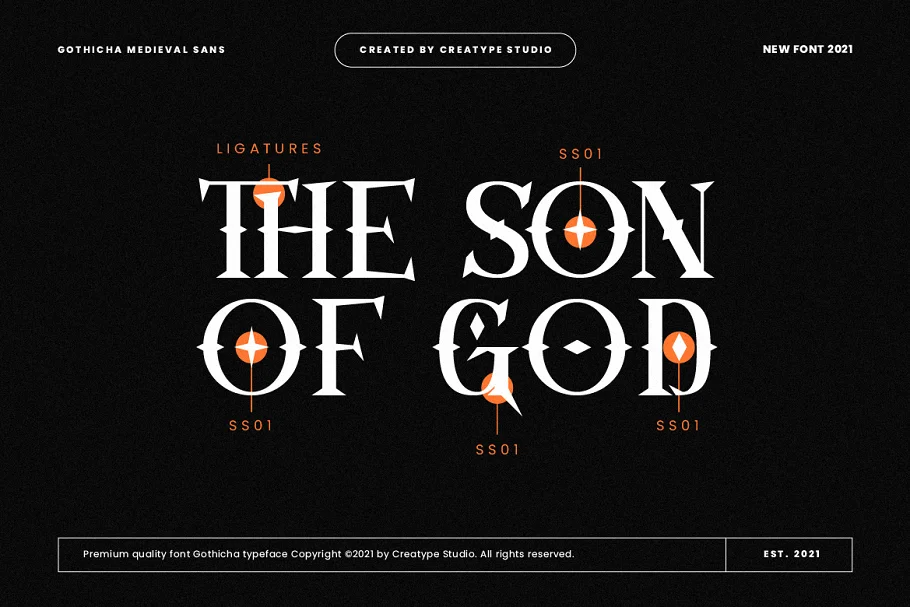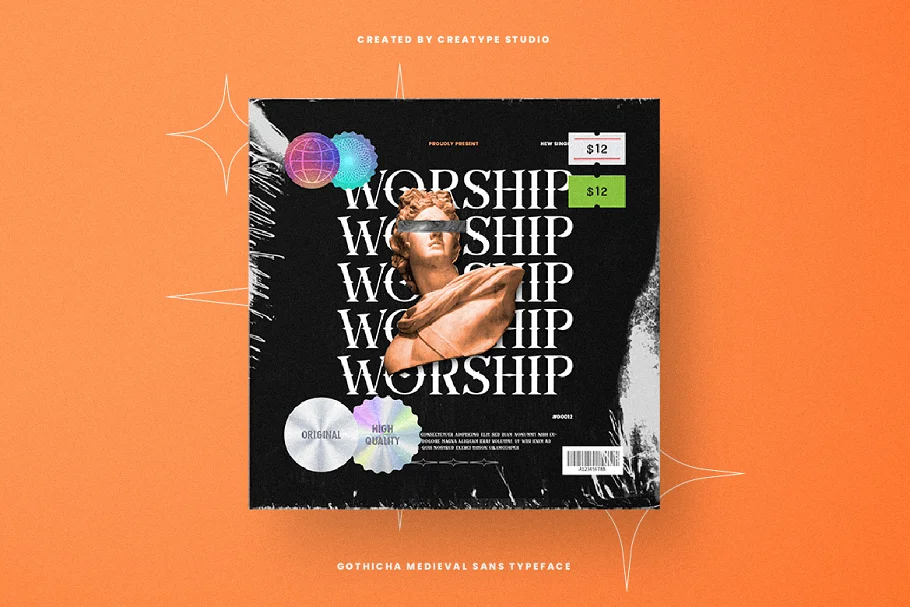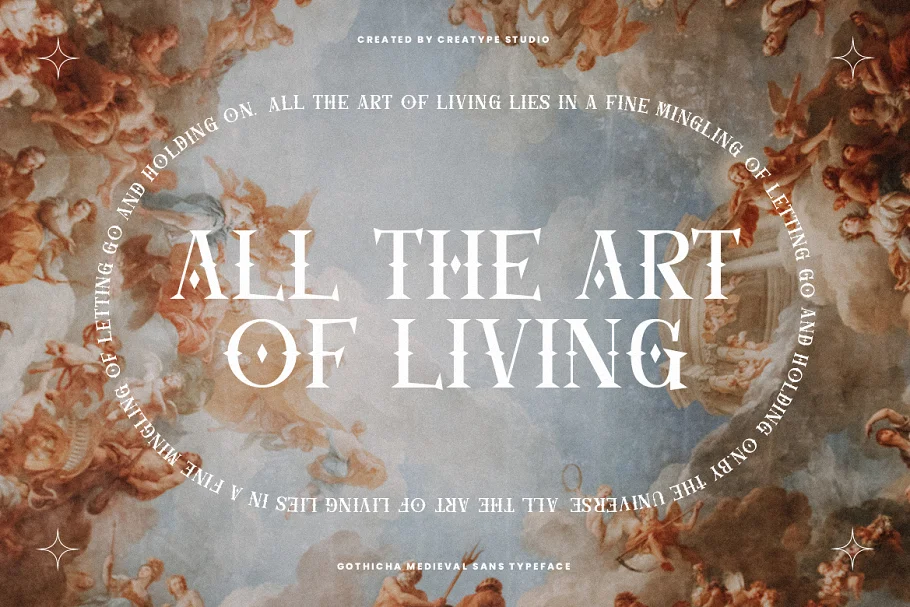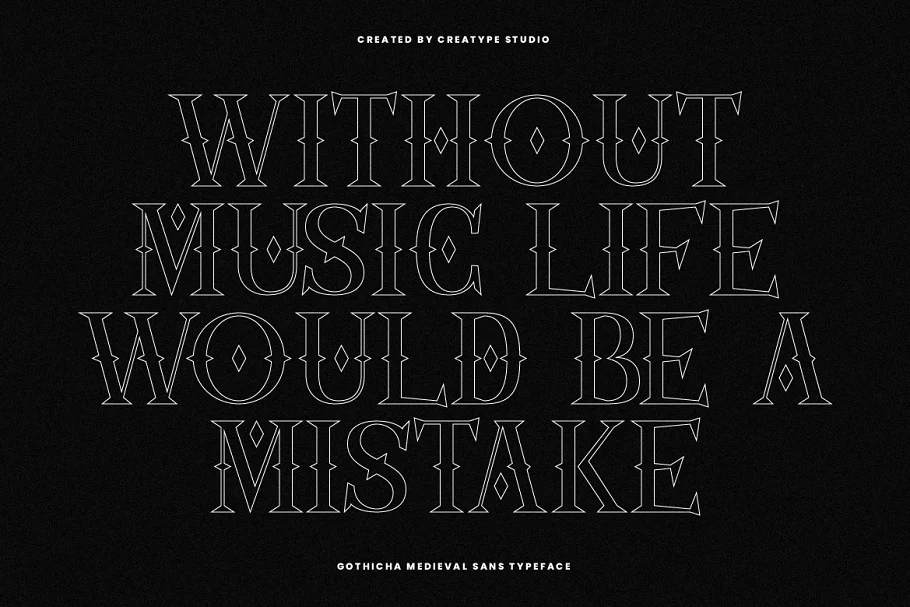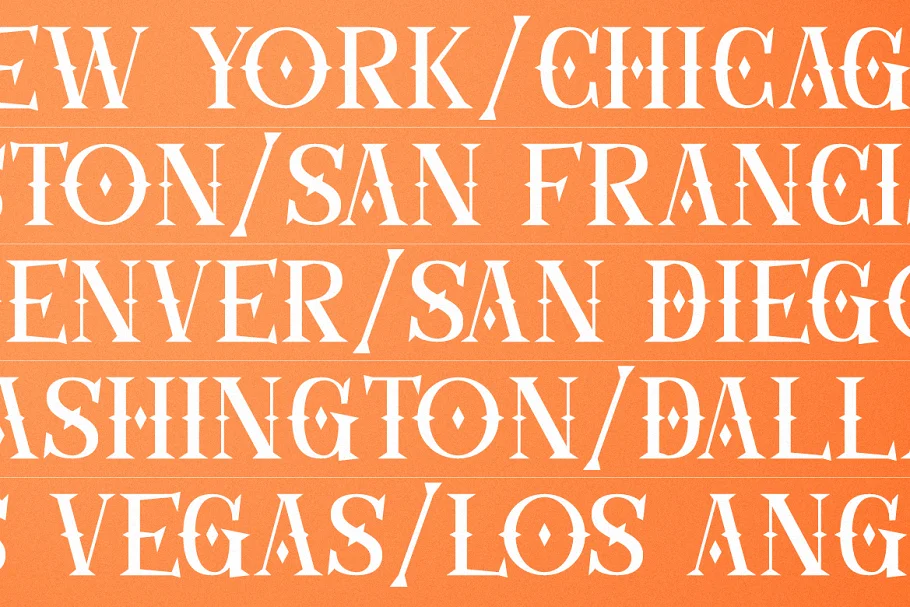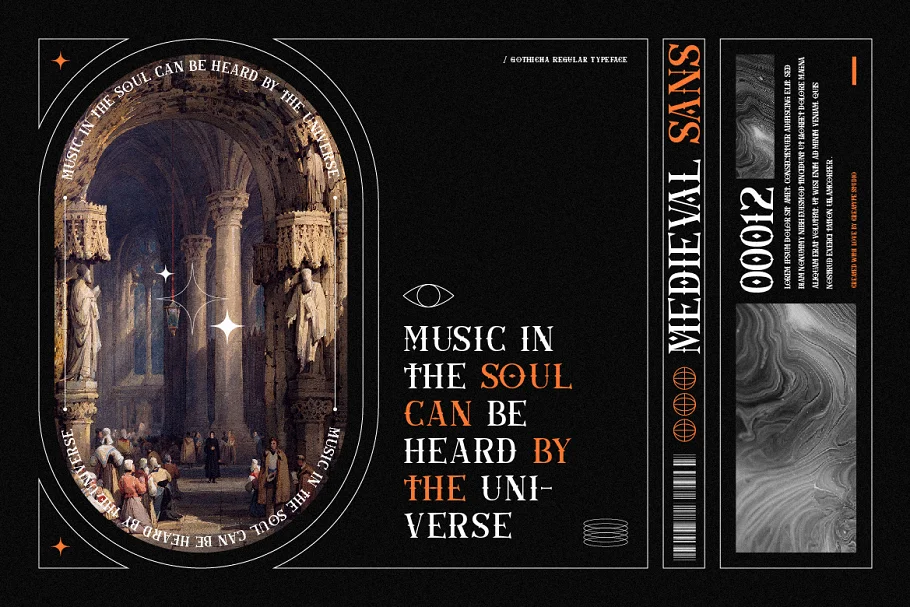
Gothicha là một kiểu chữ sans thời trung cổ được các chuyên gia chế tạo đặc biệt để tạo ra phông chữ trang nhã và chất lượng cao. Với hình dạng đẹp và đặc biệt, phông chữ này rất phù hợp cho các sản phẩm lớn của bạn.
Gothicha hoàn hảo cho các dự án xây dựng thương hiệu, logo, thiết kế đám cưới, bài đăng trên mạng xã hội, quảng cáo, bao bì sản phẩm, thiết kế sản phẩm, nhãn hiệu, nhiếp ảnh, hình mờ, thiệp mời, văn phòng phẩm và bất kỳ dự án nào cần nét chữ viết tay.
- Tấn glyphs
- Dây chằng & thay thế